Jedna nazwa potrafi prowadzić do dwóch zupełnie różnych światów. Czcionka egipcjanka może oznaczać solidny krój szeryfowy używany w typografii albo dekoracyjny font inspirowany hieroglifami, papirusami i sztuką starożytnego Egiptu. Wyjaśniam, jak rozpoznać oba znaczenia, gdzie je stosować, czym różnią się od siebie i jak wybrać rozwiązanie, które nie zdominuje całego projektu.
Dwa znaczenia jednej nazwy i praktyczne zasady wyboru
- Egipcjanka typograficzna to krój szeryfowy z mocnymi, prostokątnymi zakończeniami liter.
- Font hieroglifowy naśladuje znaki, symbole i ornamentykę starożytnego Egiptu.
- Slab serif dobrze działa w nagłówkach, plakatach, logotypach i krótkich tekstach.
- Dekoracyjne pismo egipskie najlepiej stosować oszczędnie, ponieważ szybko traci czytelność.
- Przed użyciem fontu sprawdź polskie znaki, licencję i wersje stylistyczne.
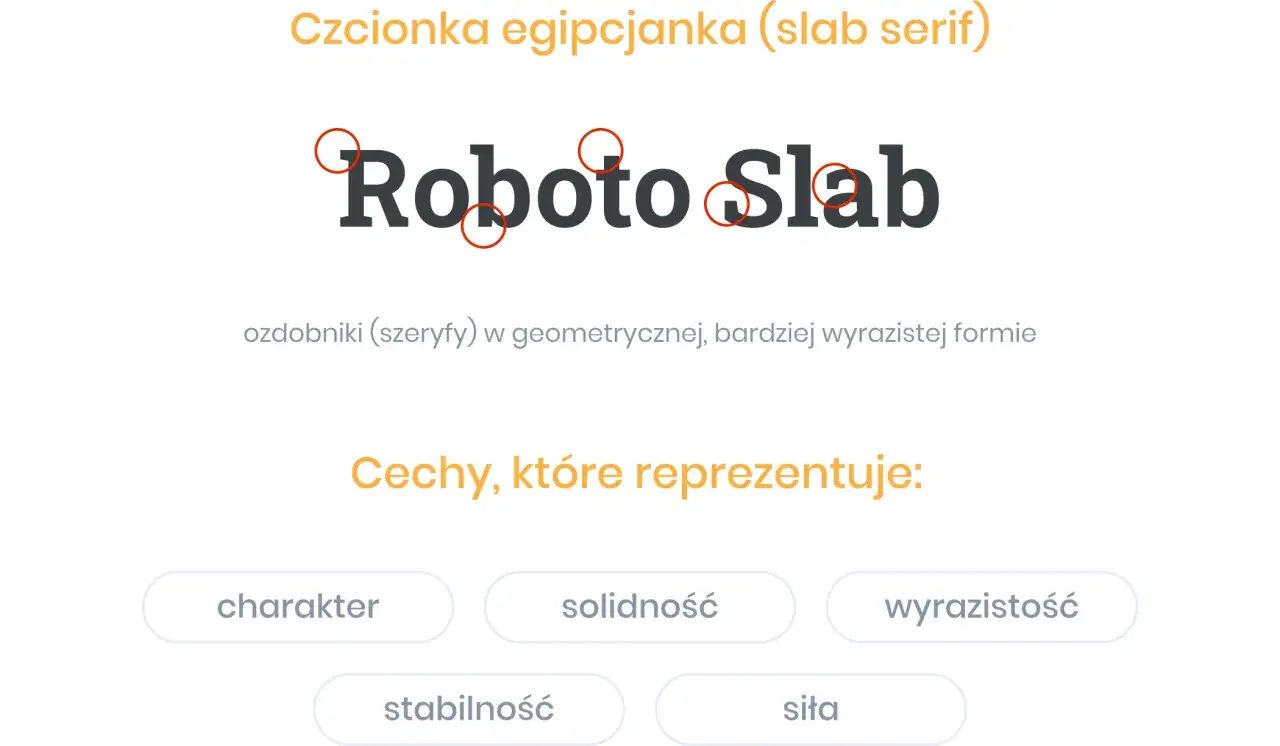
Czym właściwie jest czcionka egipcjanka
W typografii egipcjanka, nazywana też angielskim określeniem slab serif, to krój z wyraźnymi szeryfami o ciężkich, często prostokątnych kształtach. Szeryfami nazywamy krótkie zakończenia kresek liter. W tym przypadku nie są delikatnym dodatkiem, lecz mocnym elementem konstrukcji znaku.
Nazwa nawiązuje do XIX-wiecznej mody na egzotyczne skojarzenia. Nie oznacza to jednak, że krój odwzorowuje prawdziwe egipskie hieroglify. To przede wszystkim nowoczesna kategoria typograficzna, która kojarzy się z siłą, stabilnością i drukiem plakatowym.
Najłatwiej rozpoznać ją po podobnej grubości głównych kresek i szeryfów. Litery są zwykle zwarte, wyraziste i dobrze widoczne z większej odległości. W praktyce często wyglądają jak połączenie antykwy szeryfowej z prostotą kroju bezszeryfowego.
Font a krój pisma
W codziennym języku słowa „font” i „czcionka” stosuje się wymiennie, choć technicznie nie znaczą dokładnie tego samego. Krój pisma opisuje projekt liter, natomiast font jest cyfrowym plikiem, który pozwala z tego projektu korzystać w programie.
To rozróżnienie przydaje się szczególnie wtedy, gdy pobierasz plik do projektu. Dwa fonty należące do tej samej rodziny mogą różnić się grubością, szerokością, obsługą znaków diakrytycznych albo warunkami licencji.
Egipcjanka typograficzna a font inspirowany hieroglifami
Największe nieporozumienie bierze się z tego, że wyszukiwane określenie bywa używane zarówno wobec krojów slab serif, jak i ozdobnych alfabetów stylizowanych na pismo faraonów. Są to rozwiązania o zupełnie innym przeznaczeniu.
| Cecha | Egipcjanka typograficzna | Font hieroglifowy |
|---|---|---|
| Budowa | Litery alfabetu łacińskiego z ciężkimi szeryfami | Znaki obrazkowe lub stylizowane symbole |
| Czytelność | Dobra w nagłówkach i krótkich akapitach | Zwykle ograniczona, szczególnie w dłuższym tekście |
| Typowe zastosowanie | Plakaty, identyfikacja, opakowania, tytuły | Ilustracje, gry, zaproszenia, dekoracje, projekty tematyczne |
| Wrażenie | Solidność, retro, rzemiosło, wiarygodność | Egzotyka, tajemnica, archeologia, fantasy |
Jeżeli potrzebujesz normalnie zapisać polski tekst, bezpieczniejsza będzie egipcjanka alfabetowa. Font hieroglifowy często nie ma liter „ą”, „ę”, „ł” czy „ż”, a jego znaki mogą być jedynie dekoracyjnymi odpowiednikami liter, a nie prawdziwym zapisem języka staroegipskiego.
To ważne także z powodów merytorycznych. Stylizowany alfabet może wyglądać efektownie, ale nie powinien być przedstawiany jako autentyczne tłumaczenie hieroglifów. W projekcie edukacyjnym lub muzealnym lepiej jasno oddzielić inspirację wizualną od rzeczywistego systemu pisma.
Jak rozpoznać dobry krój w stylu egipcjanki
Nie każda gruba czcionka z szeryfami będzie udaną egipcjanką. Przy ocenie patrzę przede wszystkim na proporcje liter, rytm tekstu i to, czy mocne zakończenia nie utrudniają czytania.
Najważniejsze cechy
- Szeryfy belkowe są ciężkie, proste i często zbliżone grubością do głównych kresek.
- Niski kontrast oznacza niewielką różnicę między grubymi i cienkimi elementami litery.
- Wyraźna geometria nadaje znakom stabilny, uporządkowany charakter.
- Duża masa optyczna sprawia, że krój dobrze działa w tytułach i krótkich hasłach.
- Odmiany o zaokrąglonych zakończeniach są łagodniejsze i mniej „maszynowe” w odbiorze.
Warto sprawdzić szczególnie litery „a”, „g”, „R” i cyfry. To właśnie one szybko pokazują, czy font jest dopracowany, czy tylko obciążono zwykły krój grubą kreską. W mojej praktyce lepiej wypadają rodziny z kilkoma grubościami niż pojedynczy, bardzo ciężki wariant.
Do dłuższych akapitów wybieram odmiany regularne lub medium, zwykle w rozmiarze około 10-12 punktów w druku. Najgrubsze wersje zostawiam na nagłówki, etykiety i krótkie komunikaty, bo przy większej ilości tekstu szybko tworzą ciemną, męczącą plamę.
Gdzie stosować ten styl, żeby pracował na korzyść projektu
Egipcjanka typograficzna dobrze pasuje do projektów, które mają wyglądać konkretnie, solidnie i trochę retro. Jej charakter sprawdza się tam, gdzie litera ma być nie tylko nośnikiem informacji, lecz także wyraźnym elementem kompozycji.
Jeśli zależy Ci na wiarygodnym efekcie, nie kopiuj bezrefleksyjnie przypadkowych symboli znalezionych w internecie. Zadbaj o jasne rozróżnienie między historycznym pismem a współczesną stylizacją. Dobra typografia nie tylko przyciąga wzrok, lecz także uczciwie komunikuje treść.
Właśnie dlatego w większości projektów polecam zacząć od czytelnego kroju slab serif, a dopiero później dodawać egipskie akcenty. Taki kierunek daje więcej kontroli, lepiej działa w druku i na ekranie, a przede wszystkim pozwala zachować równowagę między atmosferą a funkcją.